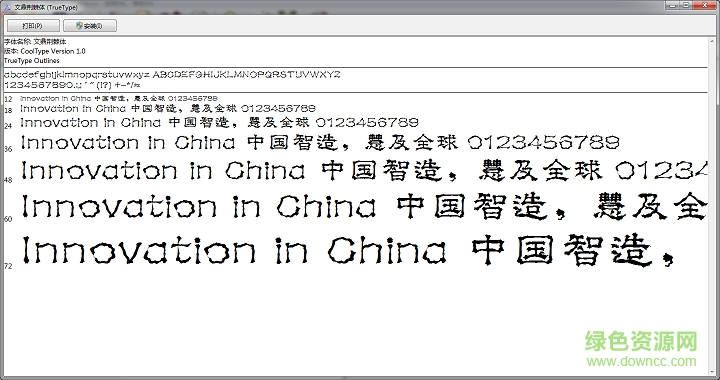
jingjieg medium gb
jingjieg medium gb是一款適合用作藝術(shù)創(chuàng)作的中文字體,這款字看上去就會(huì)讓人覺得扎心,非常的有視覺沖擊力,有需要的朋友歡迎下載!
jingjieg medium gb簡(jiǎn)介
jingjieg字體是文鼎字庫中的文鼎荊棘體,這款字體采用隸書的風(fēng)格,但是在筆畫上加入不規(guī)整的特色,看上去充滿了刺,非常的有特點(diǎn)!